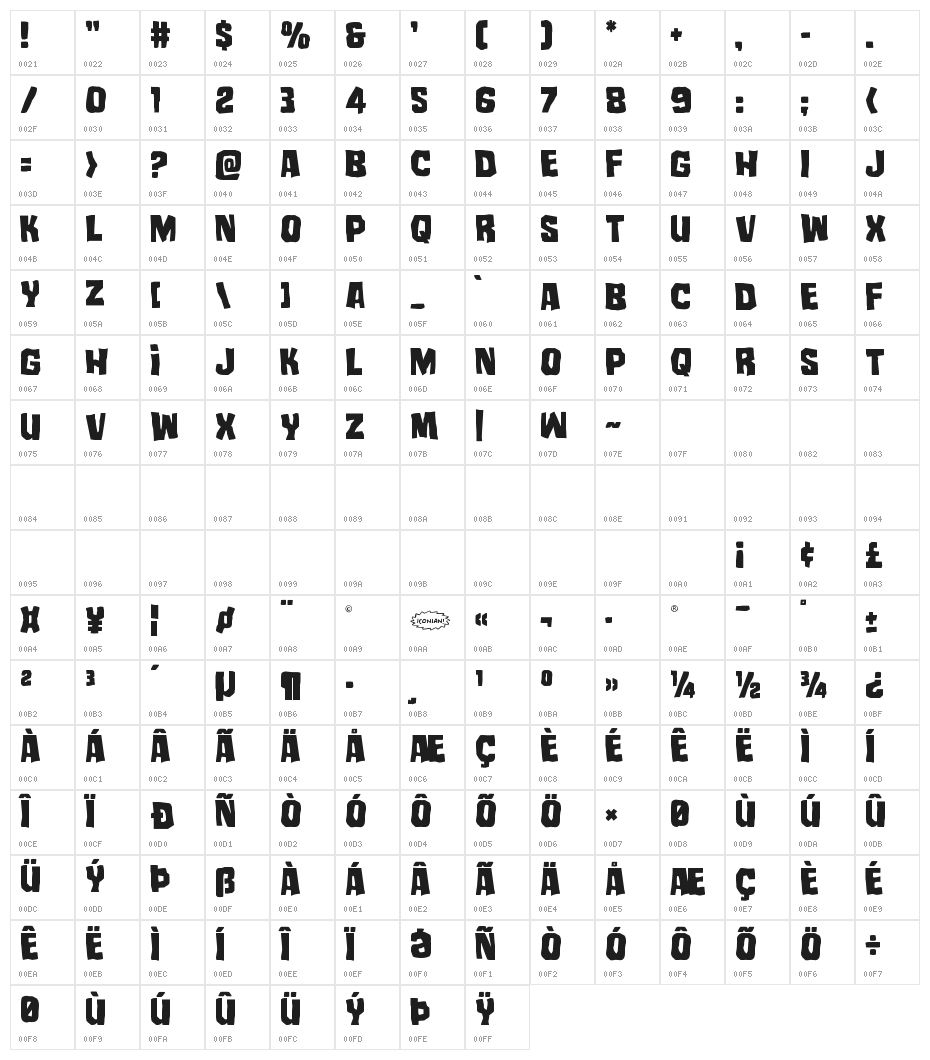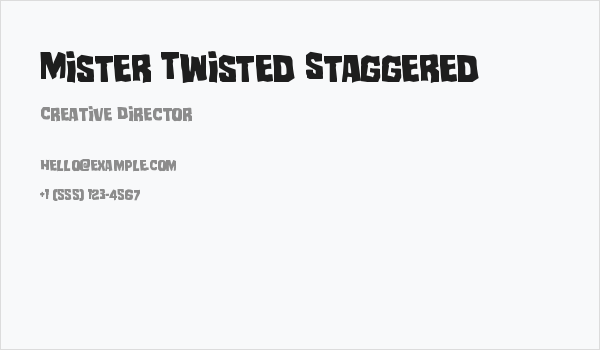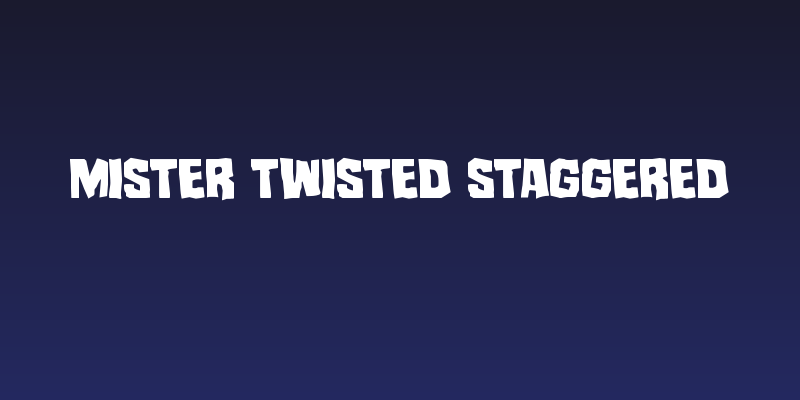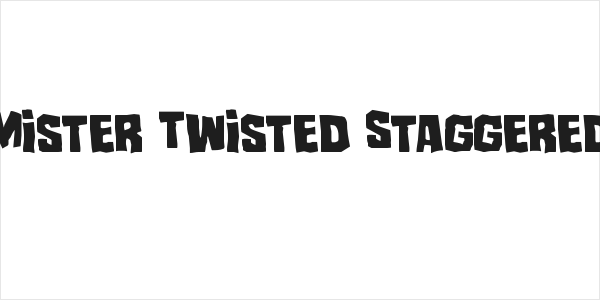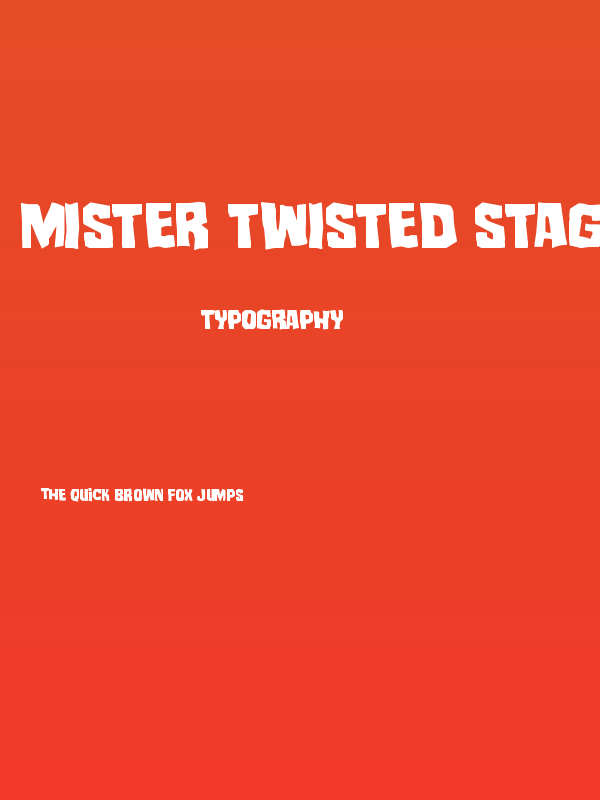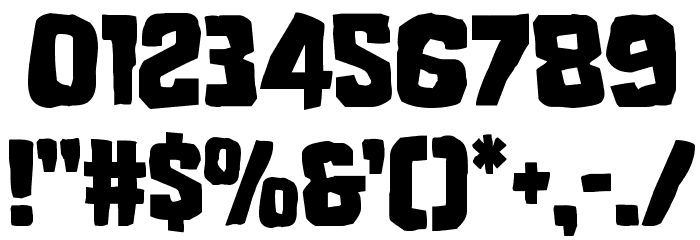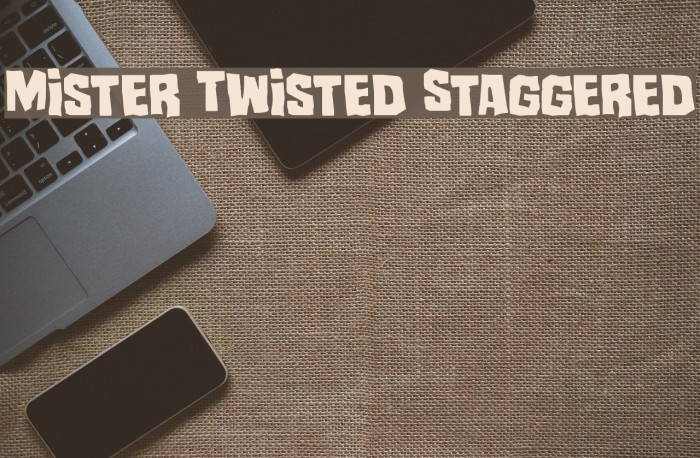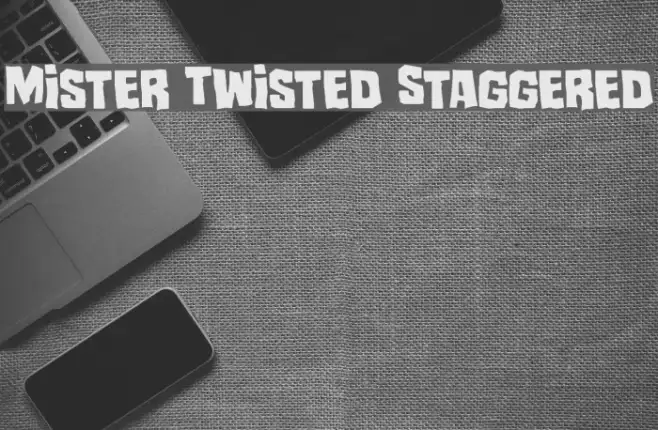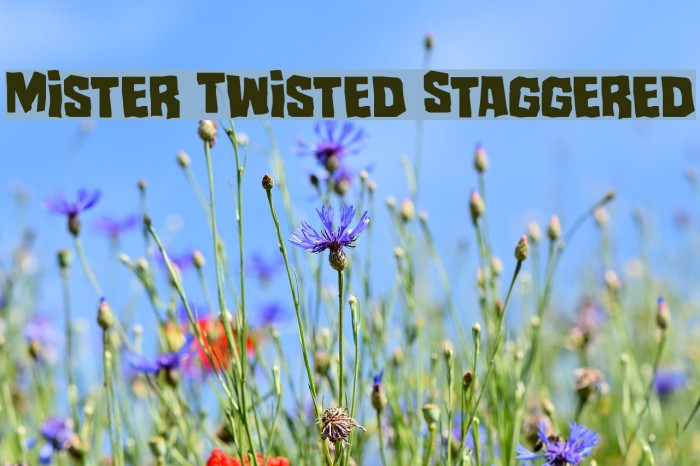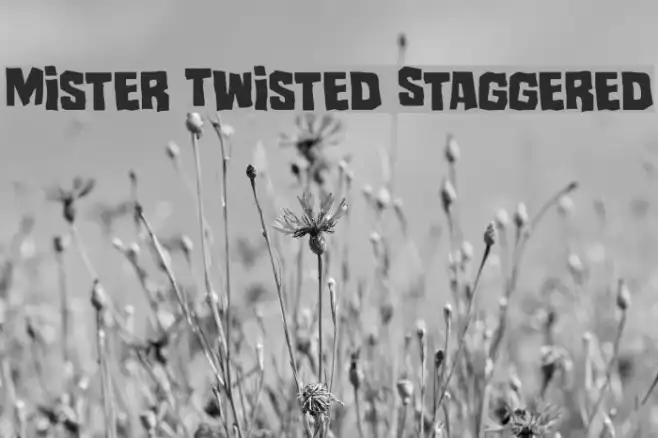
Mister Twisted Staggered Font
| Proyectos propuestos | Ideal for posters, event flyers, children's book covers, and any creative project that needs a lively and unconventional typeface. |